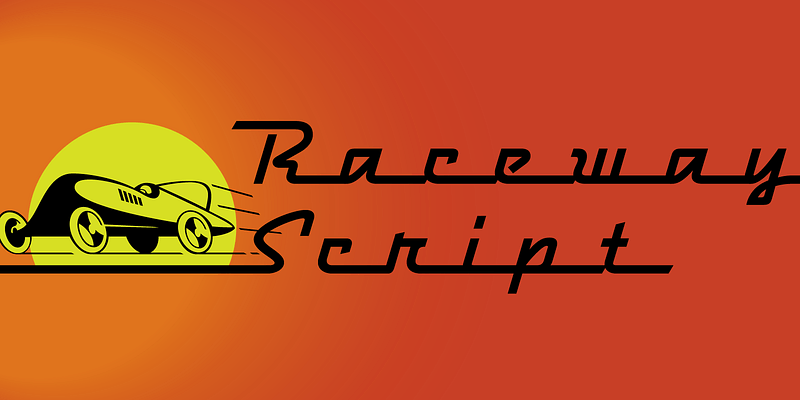
Raceway de Leslie Cabarga s’inspire des lettres 3D en contreplaqué sciées au gabarit, automatiquement espacées et alignées sur une planche à encoches par le trait de ligature. La grande régularité des traits et des courbes s’allie avec l’omniprésence des lignes horizontales pour créer une superbe police de style Art déco. La réutilisation habile de cet interlettrage d’une largeur naïve qui faisait fureur dans les années 1930 devrait garantir à cette police toute sa place dans la collection des créateurs passionnés de décoration rétro ; FB 1995
Zavier Cabarga a dessiné des images et des caractères toute sa vie. « Le dessin exige une perception inhérente de l’anatomie et de la proportion. Il en va de même pour la typographie, car je crois que nos anciennes lettres sont basées sur les proportions humaines », explique Zavier. « C’est d’abord les bandes dessinées qui m’ont inspiré, puis j’ai commencé à copier des logos et des caractères de titrage que je trouvais dans des magazines. À 15 ans, j’ai décapé des négatifs pour former une police de photocomposition brute mais utilisable. »
Travaillant sous le nom Handy Lettering Co. pendant de nombreuses années, Zavier a créé des caractères à la main pour des clients du secteur de la publicité tout en travaillant à temps plein comme illustrateur. « Dessiner des illustrations a toujours semblé difficile, alors qu’écrire, c’est facile et amusant », explique Zavier. « Je travaille depuis 25 ans sur Macintosh, ce qui m’a permis de créer des polices d’ordinateur, ce qui, à bien des égards, est la chose la plus satisfaisante que je fasse. Taper une lettre ou un caractère manuscrit avec une police que j’ai créée me donne l’impression d’être Dieu ».